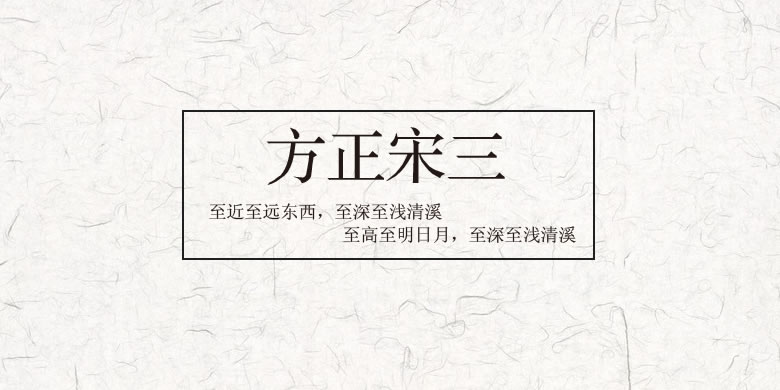
方正宋三
字体品牌: 方正字库 设计师:方正字库 字体分类:宋体 字体属性:基础字 字符集:大陆简体(GB2312-80)、简繁扩展(GBK) 发布时间: 1996
宋三当属现代电脑宋体字的“前辈”。如果放大后仔细观察,我们会发现宋三是没有曲线的,撇捺点这样圆转的笔画都由直线段拼接而成。这是因 为在早期激光照排制版时代,电脑运算能力和存储容量低,直线段字体占有的数据量小,电脑解析迅速。即使在今天,对嵌入式设备来说,直线段字体仍然更易于解析显示。方正宋三的风格中庸平和,适用于文学类的正文排版,文本秀丽、阅读醒目。